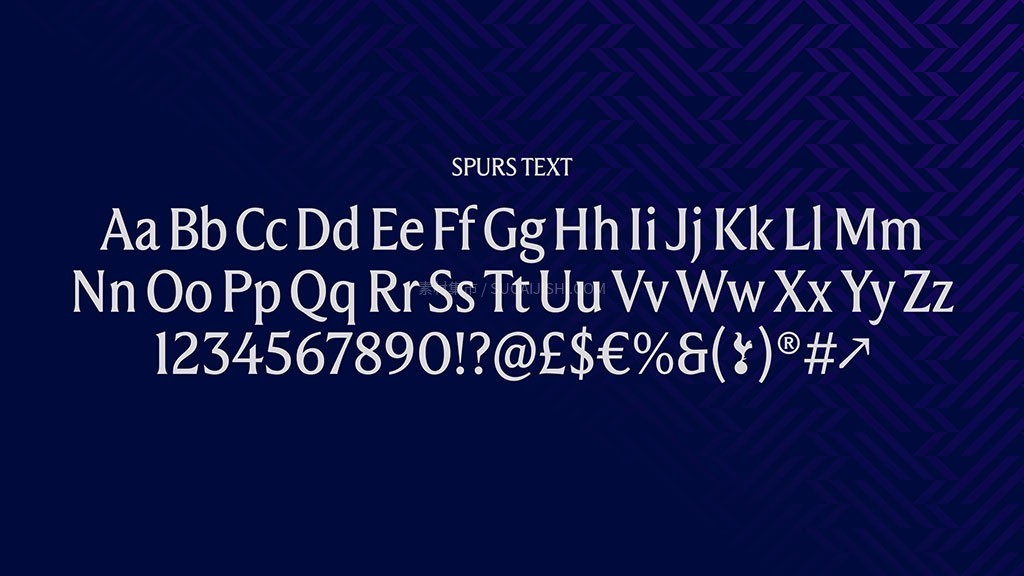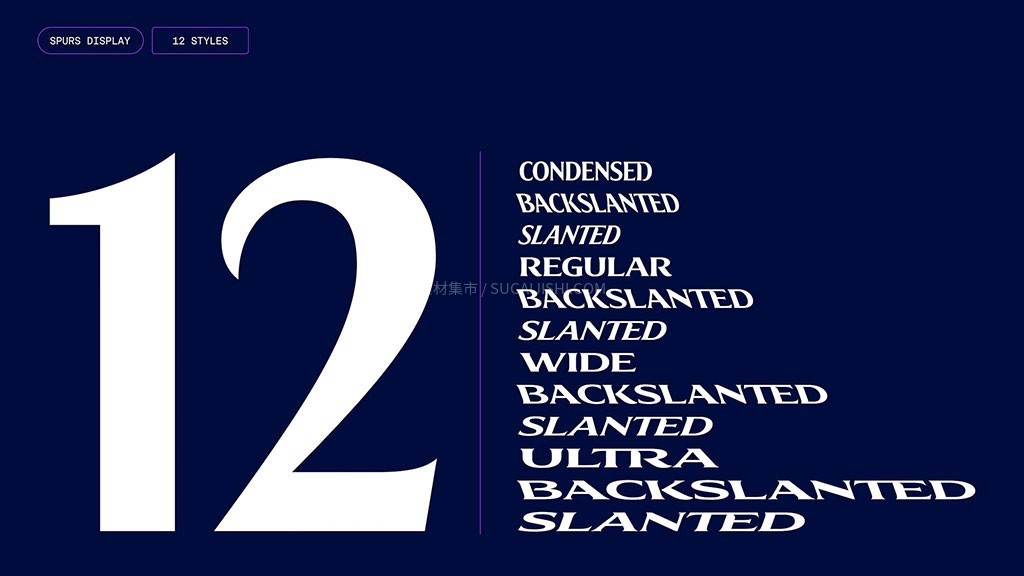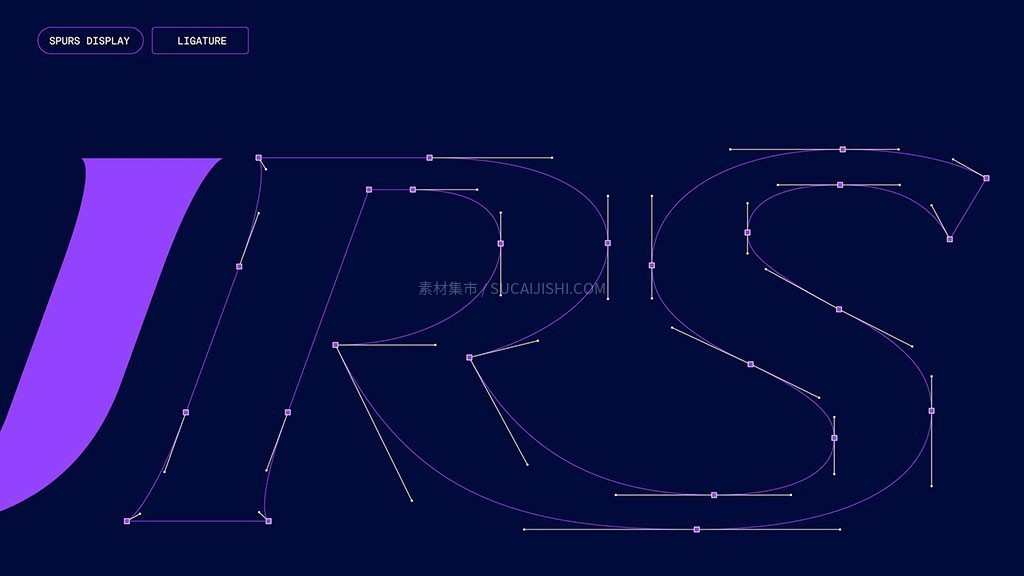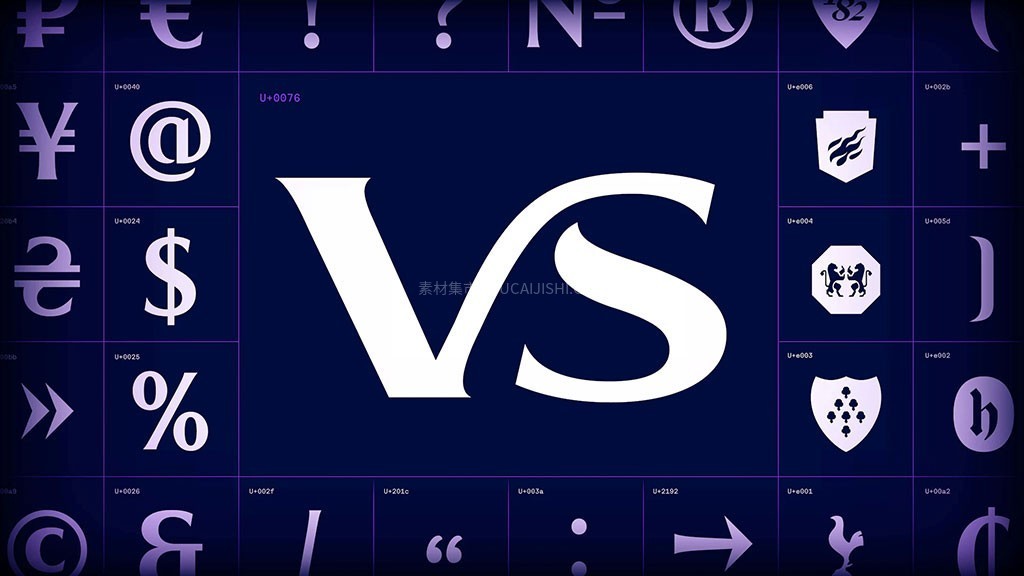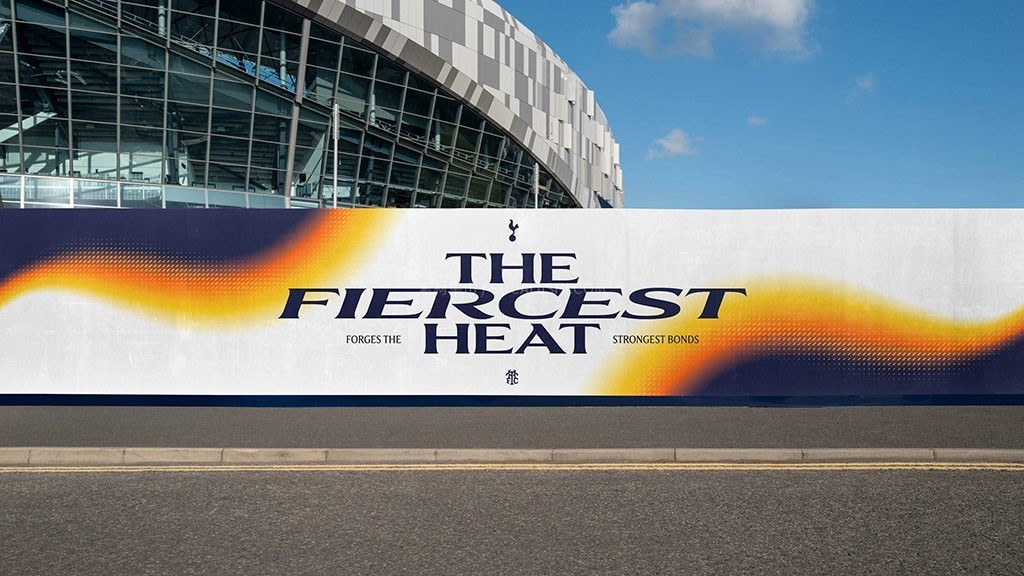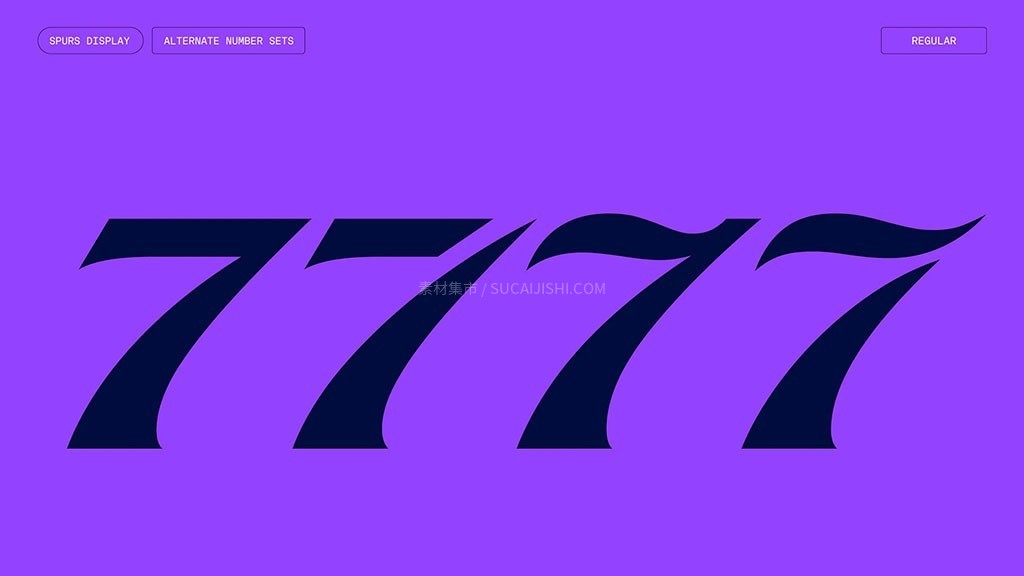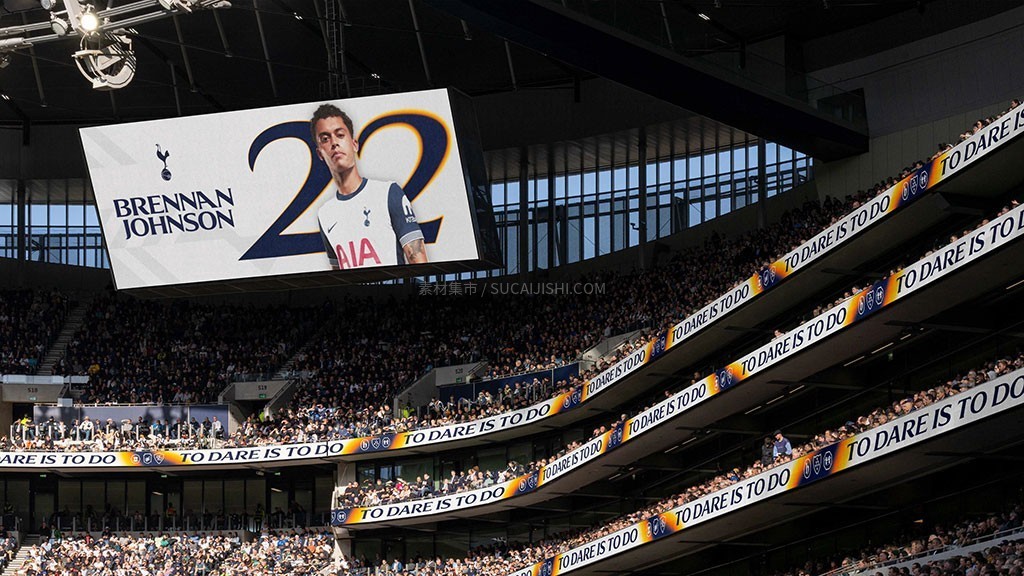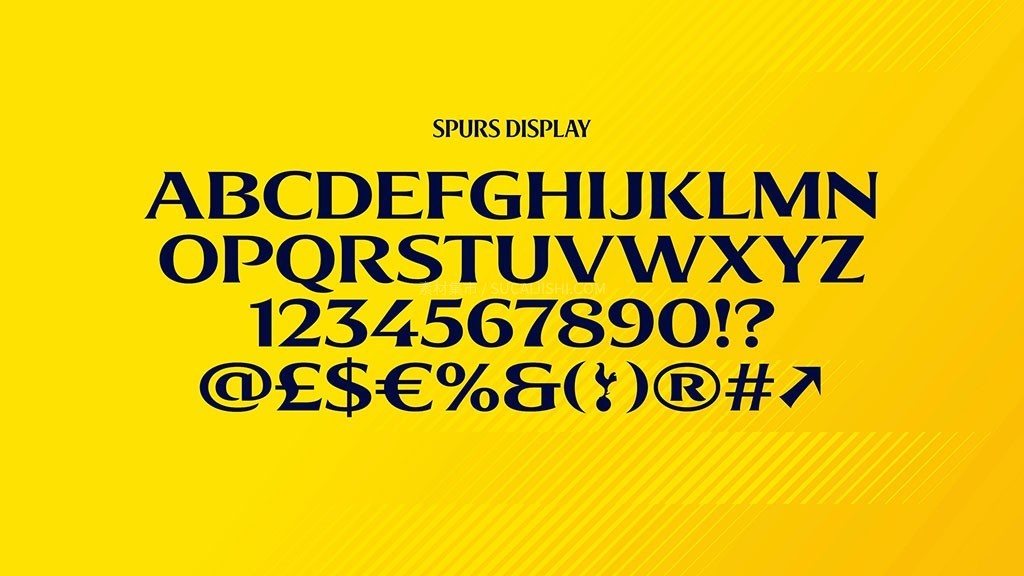
托特纳姆热刺官方定制字体
这套由 F37® 为托特纳姆热刺足球俱乐部量身定制的英文字体真的太燃了!整套字库包含了12种不同的字重和样式,设计灵感直接拉满——巧妙融入了热刺标志性的公鸡Logo元素。它不仅保留了超经典的“TH”大写字母骨架,还全新加入了极具现代感的小写字母、特殊字符和连字效果。整体风格活力四射、动感十足,完美契合“敢为即成”的运动精神。如果你的项目需要一种充满能量、极具辨识度的视觉冲击力,这套灵活性极高的字体绝对能为你的设计注入满格的活力与未来感!